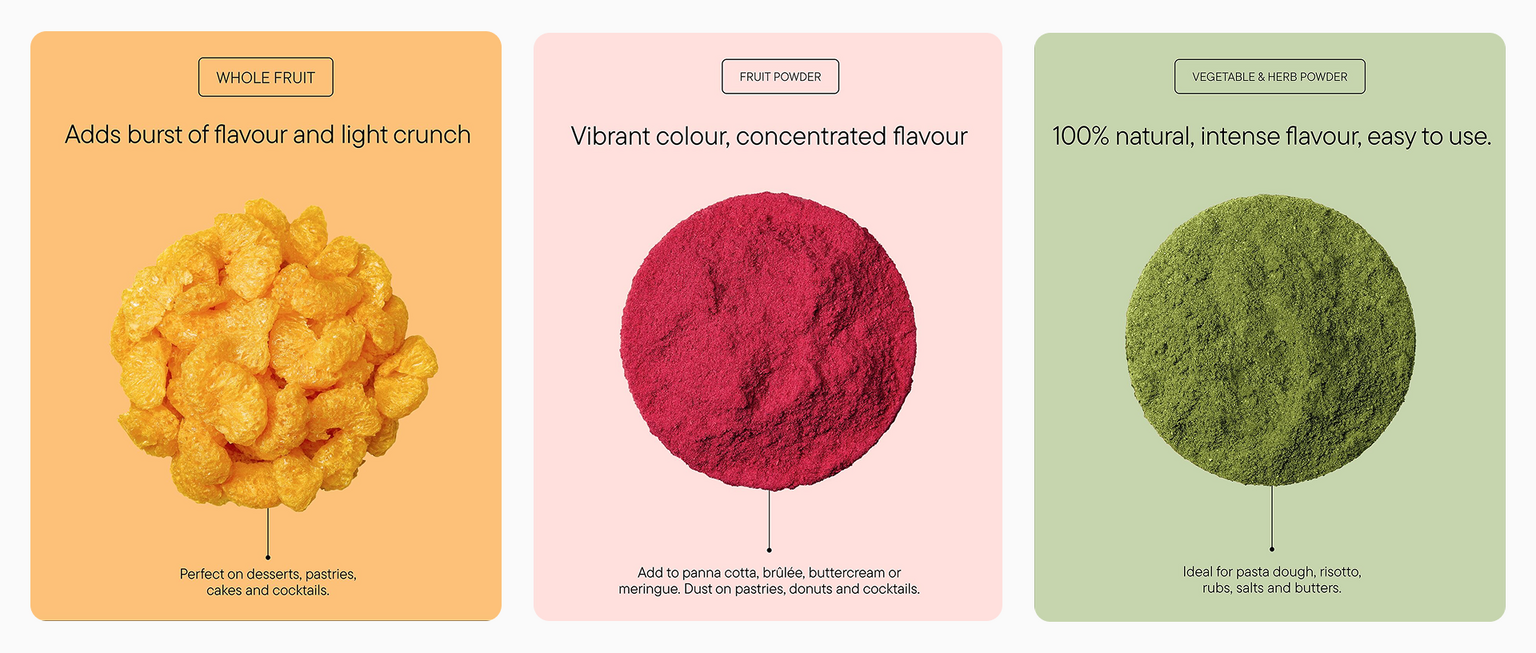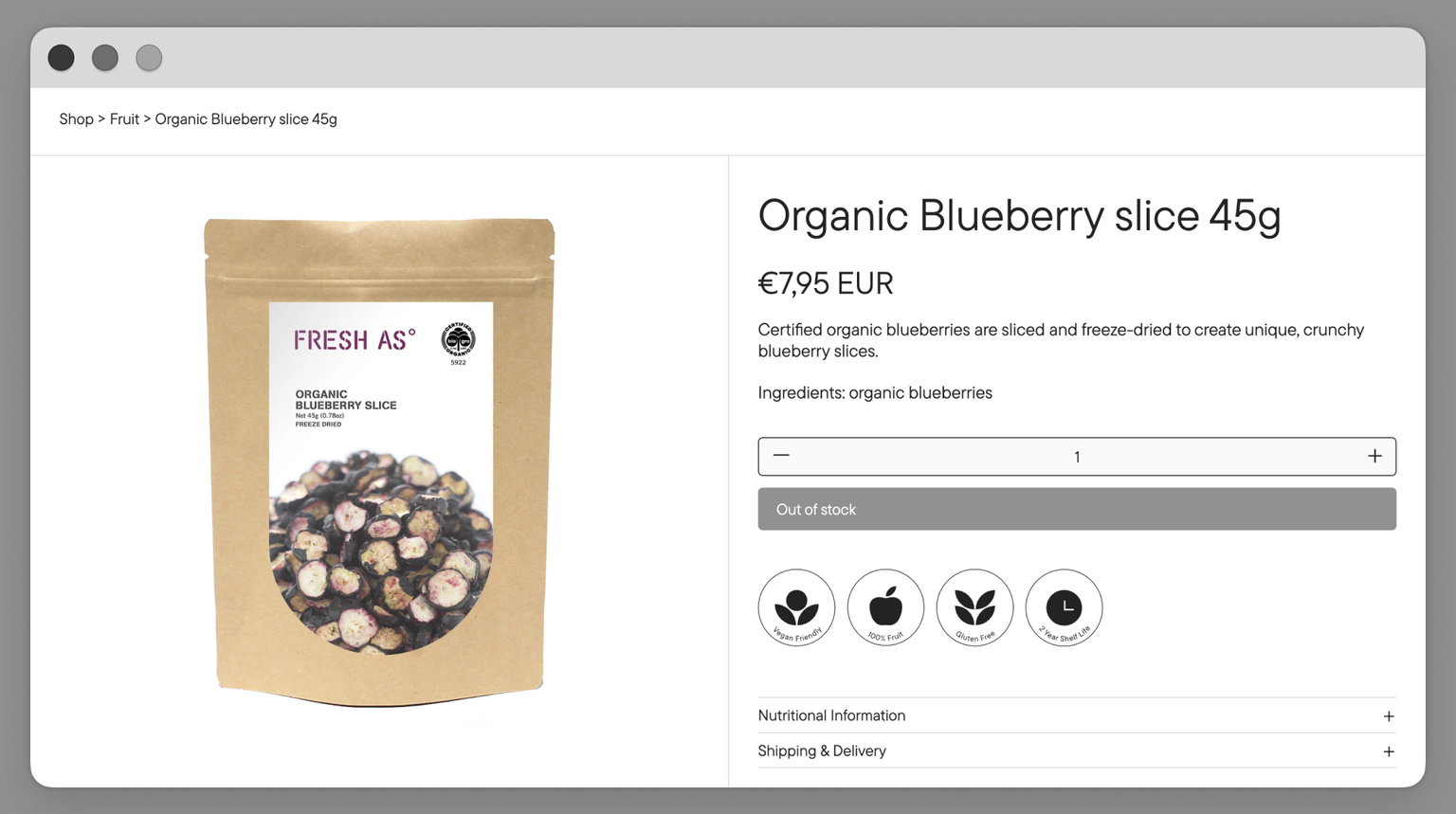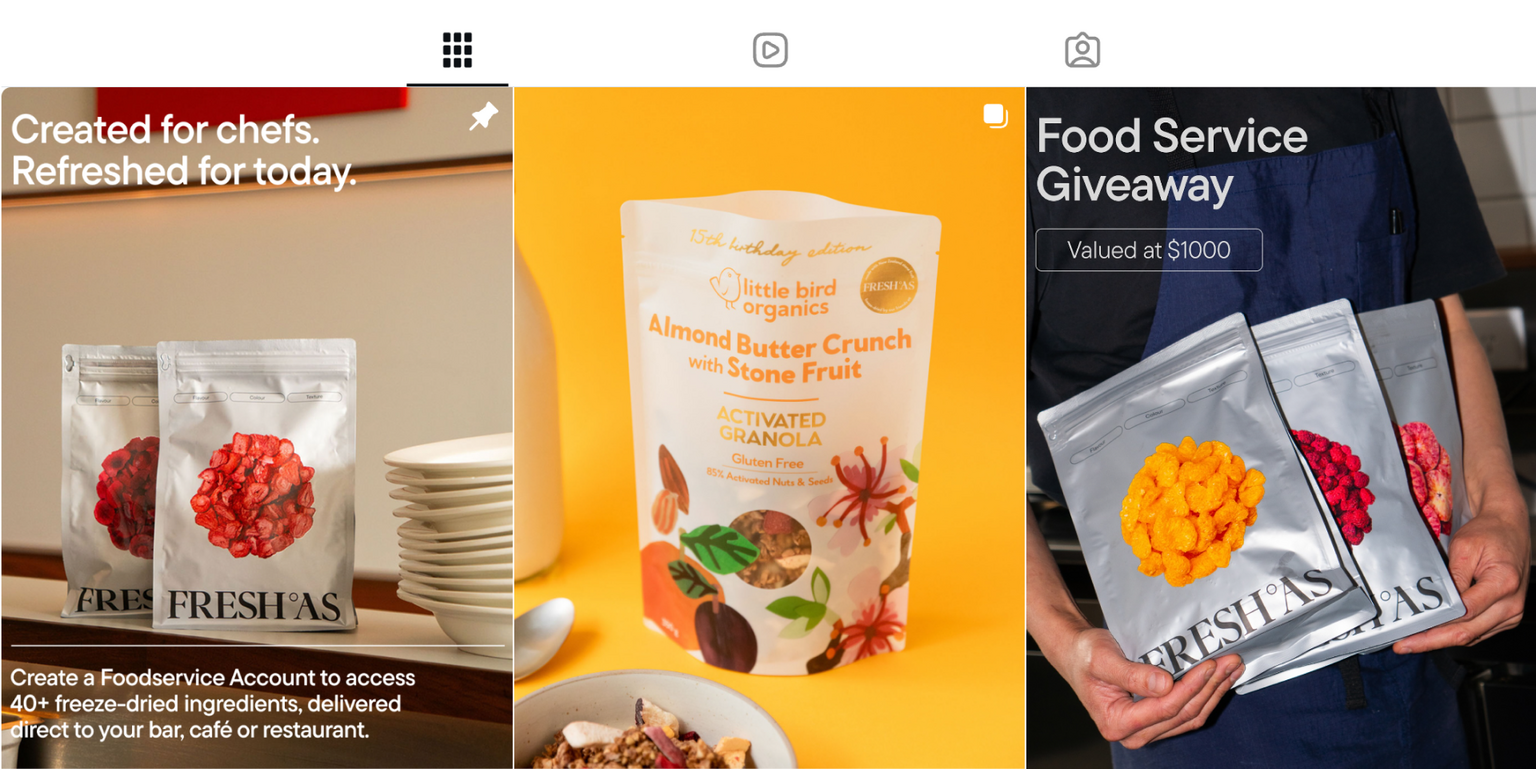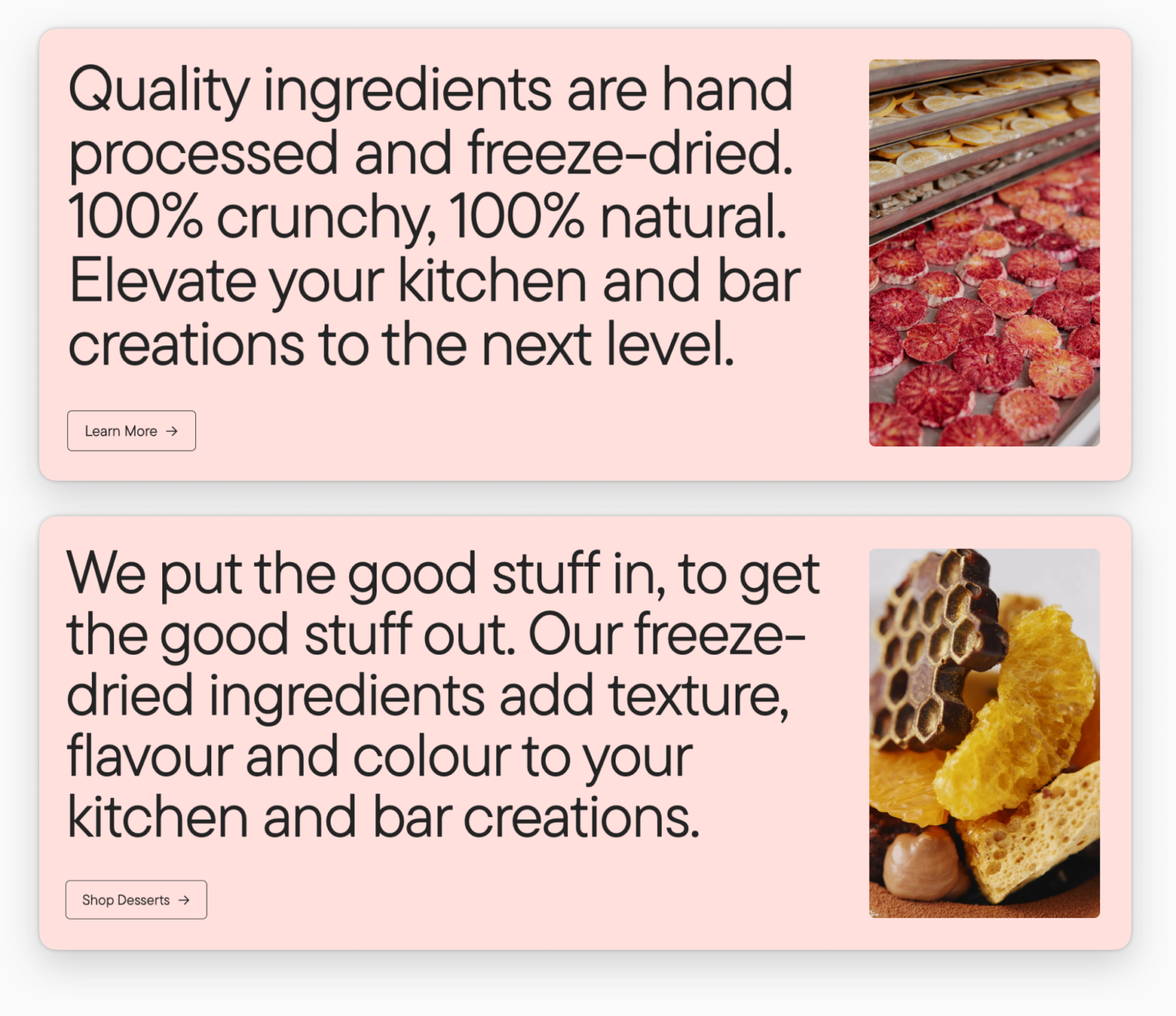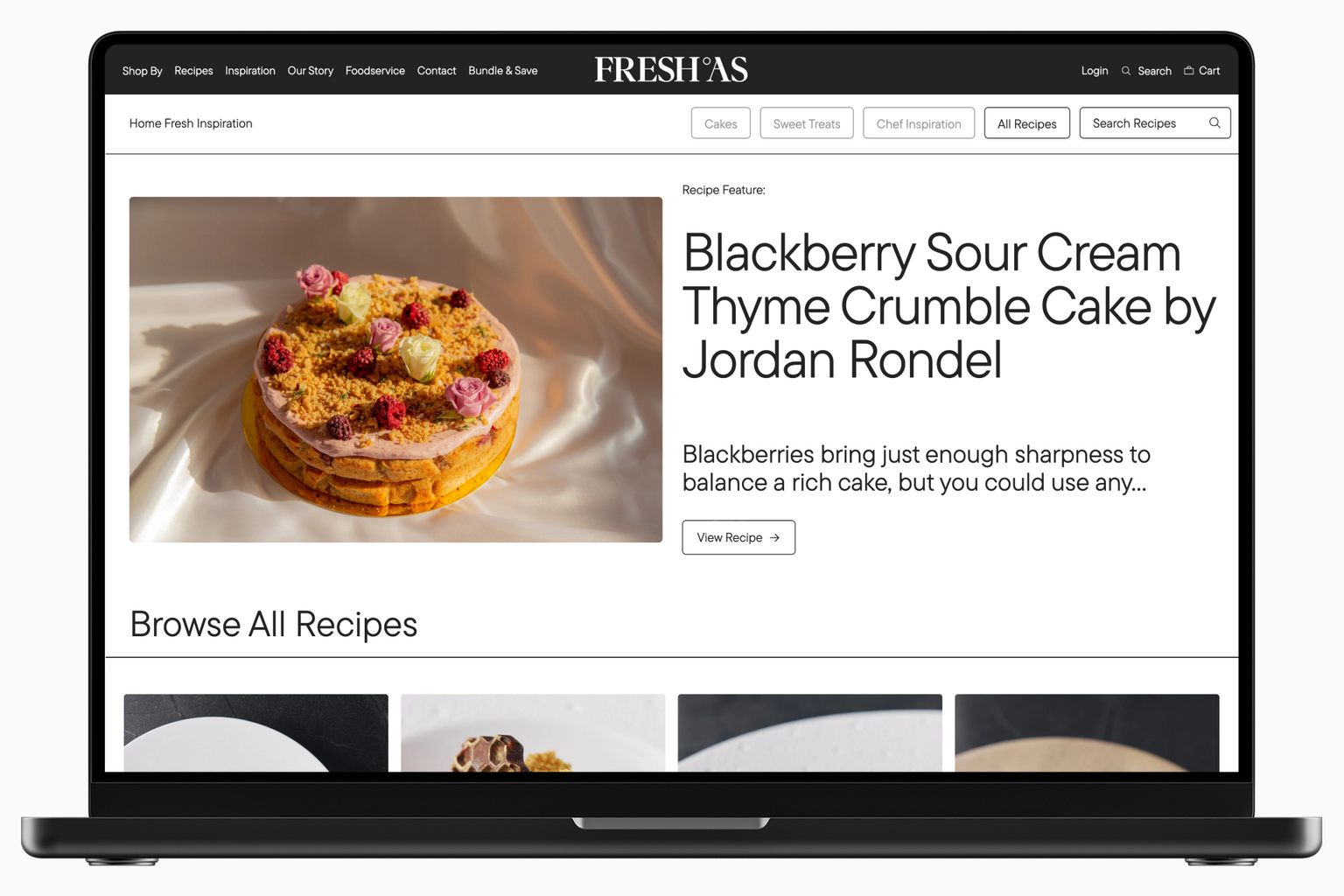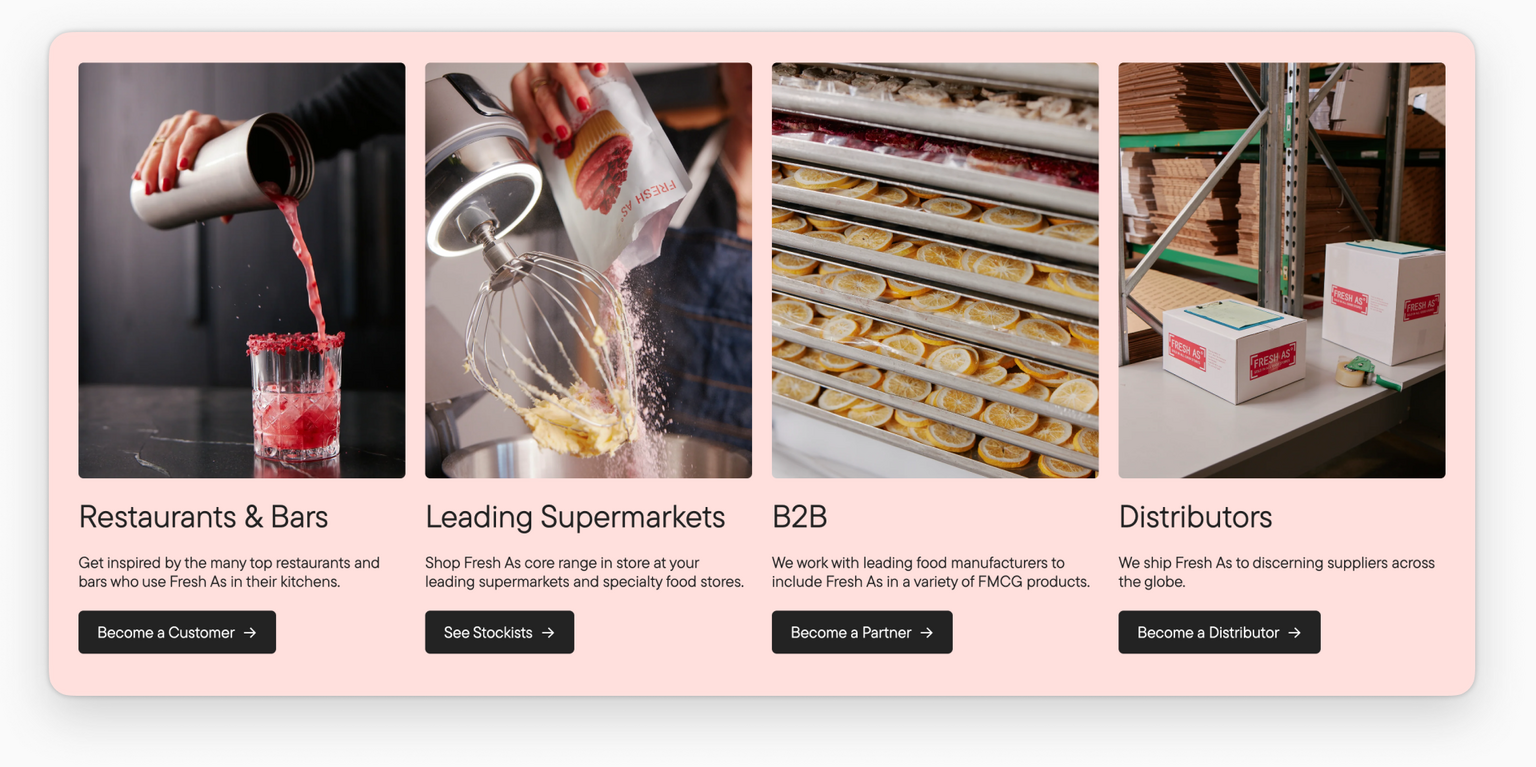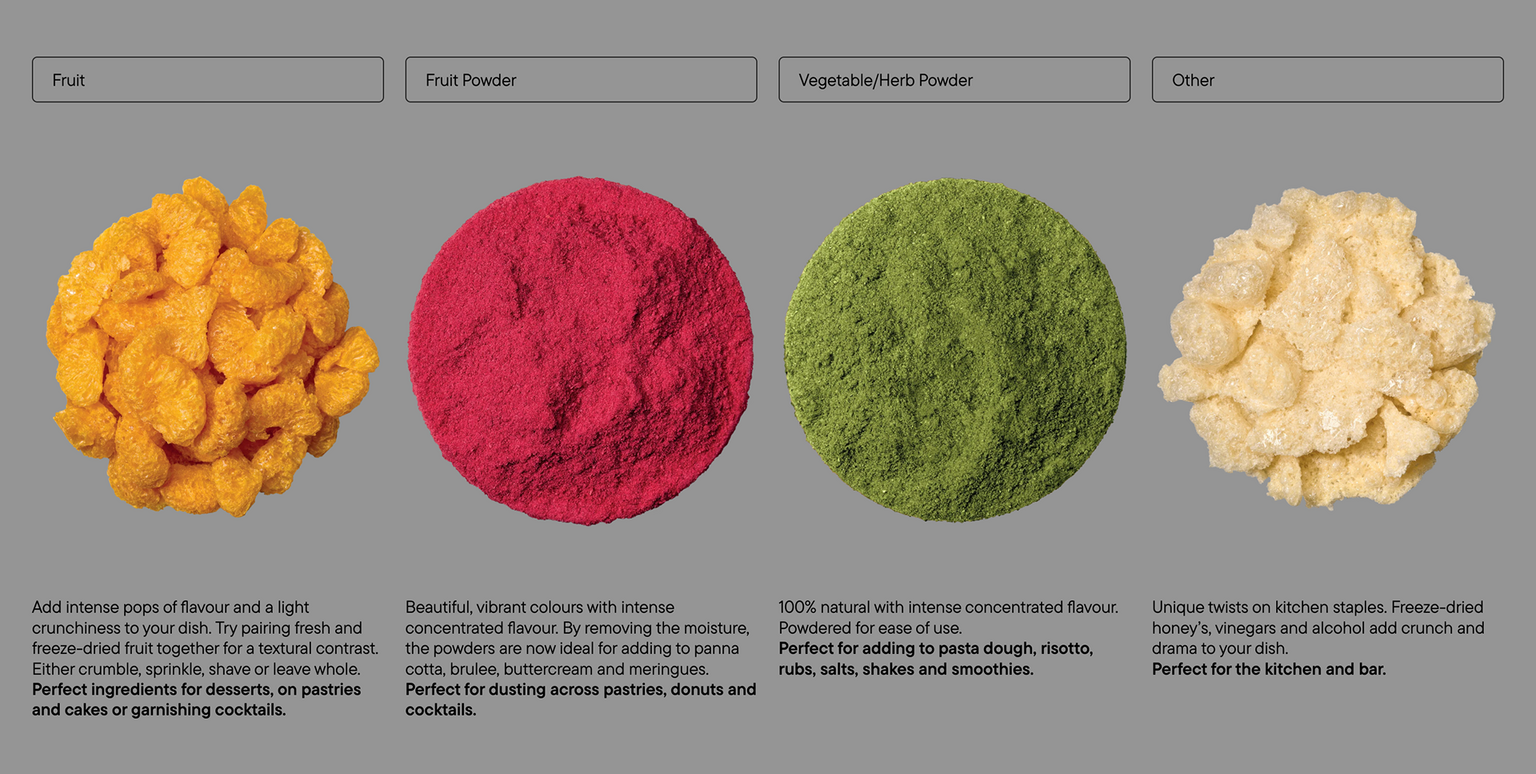
Универсальный TT Commons™ Pro стал частью фирменного стиля компании Fresh As.
Fresh As — новозеландская семейная компания, которая более 20 лет производит сублимированные фрукты, овощи и другие ингредиенты для ресторанов, баров, магазинов и производителей продуктов питания. Компания делает акцент на натуральных продуктах, насыщенном вкусе и цвете, а также современных технологиях сублимации. TT Commons™ Pro органично вписался в яркую и современную айдентику Fresh As. Лаконичный шрифт уравновесил насыщенный визуальный контент, сделав стиль бренда более собранным.